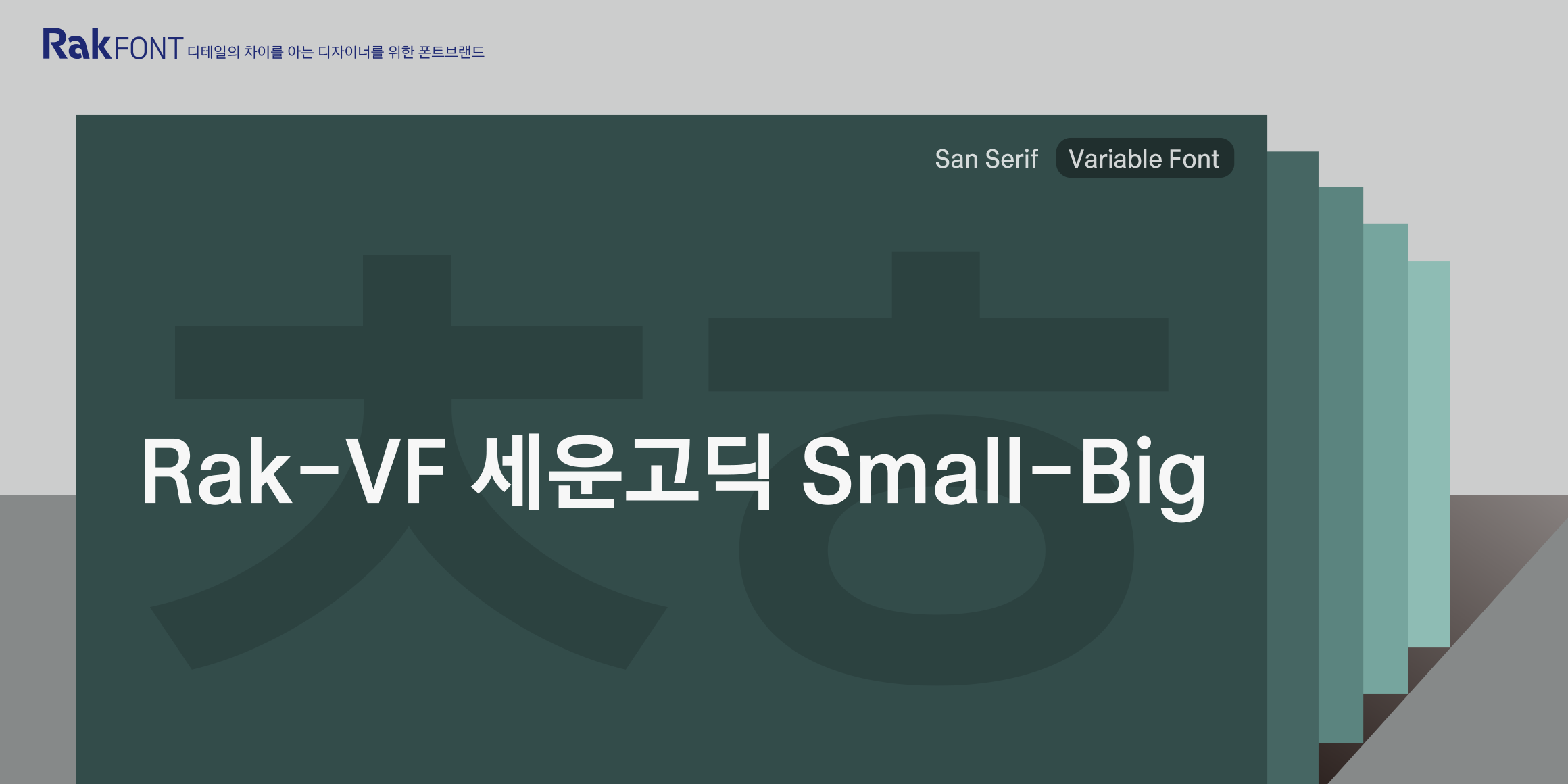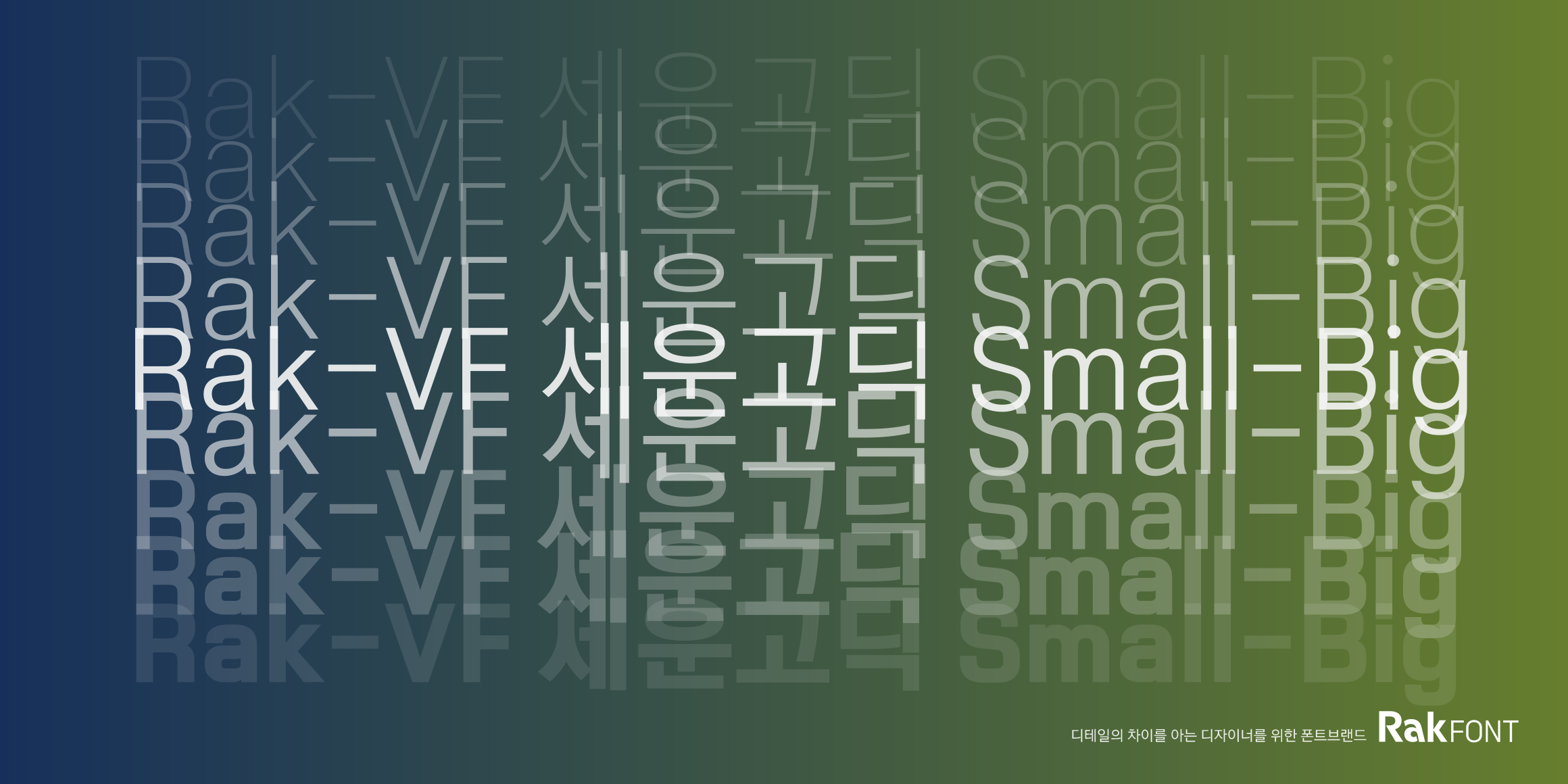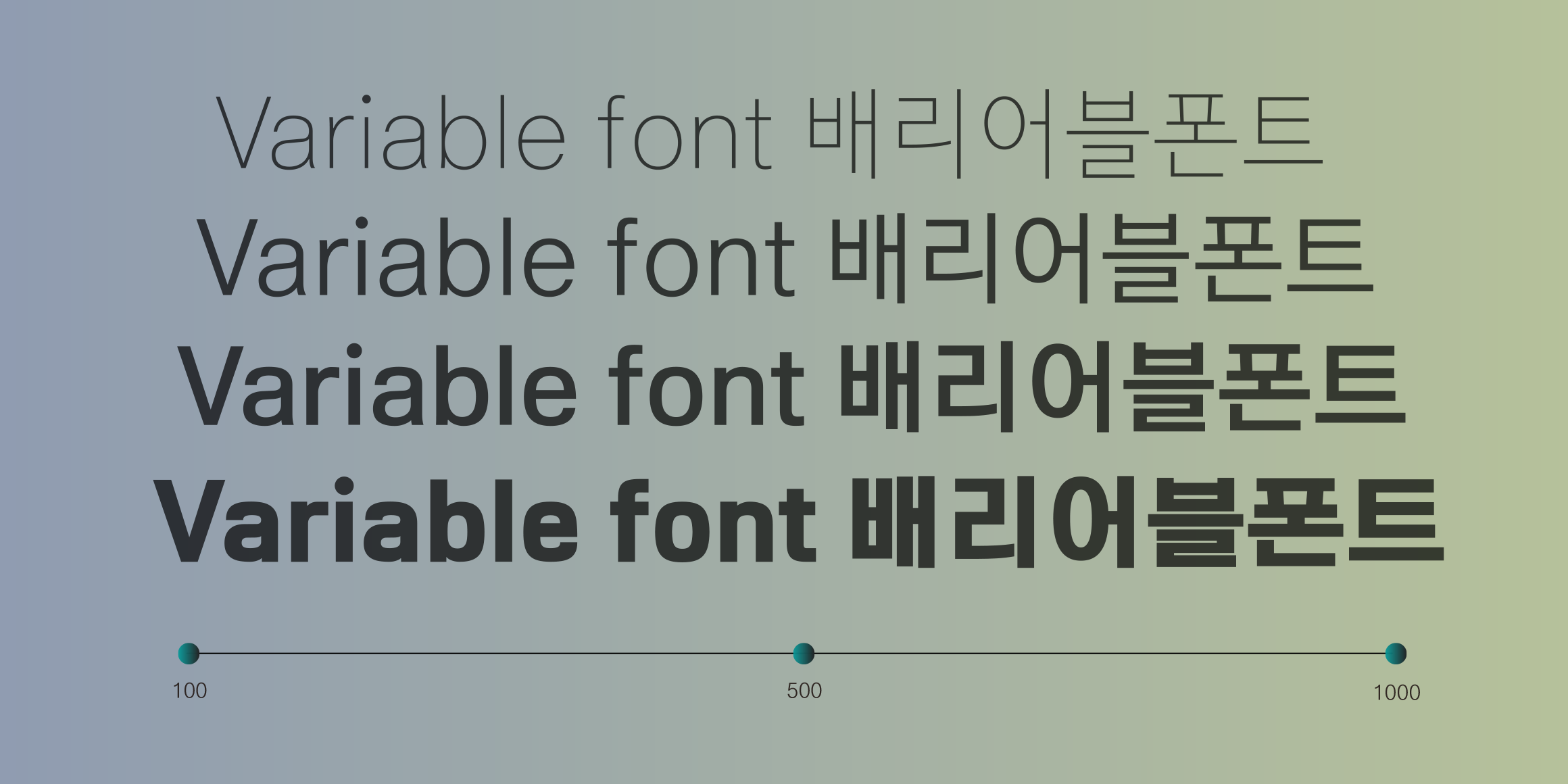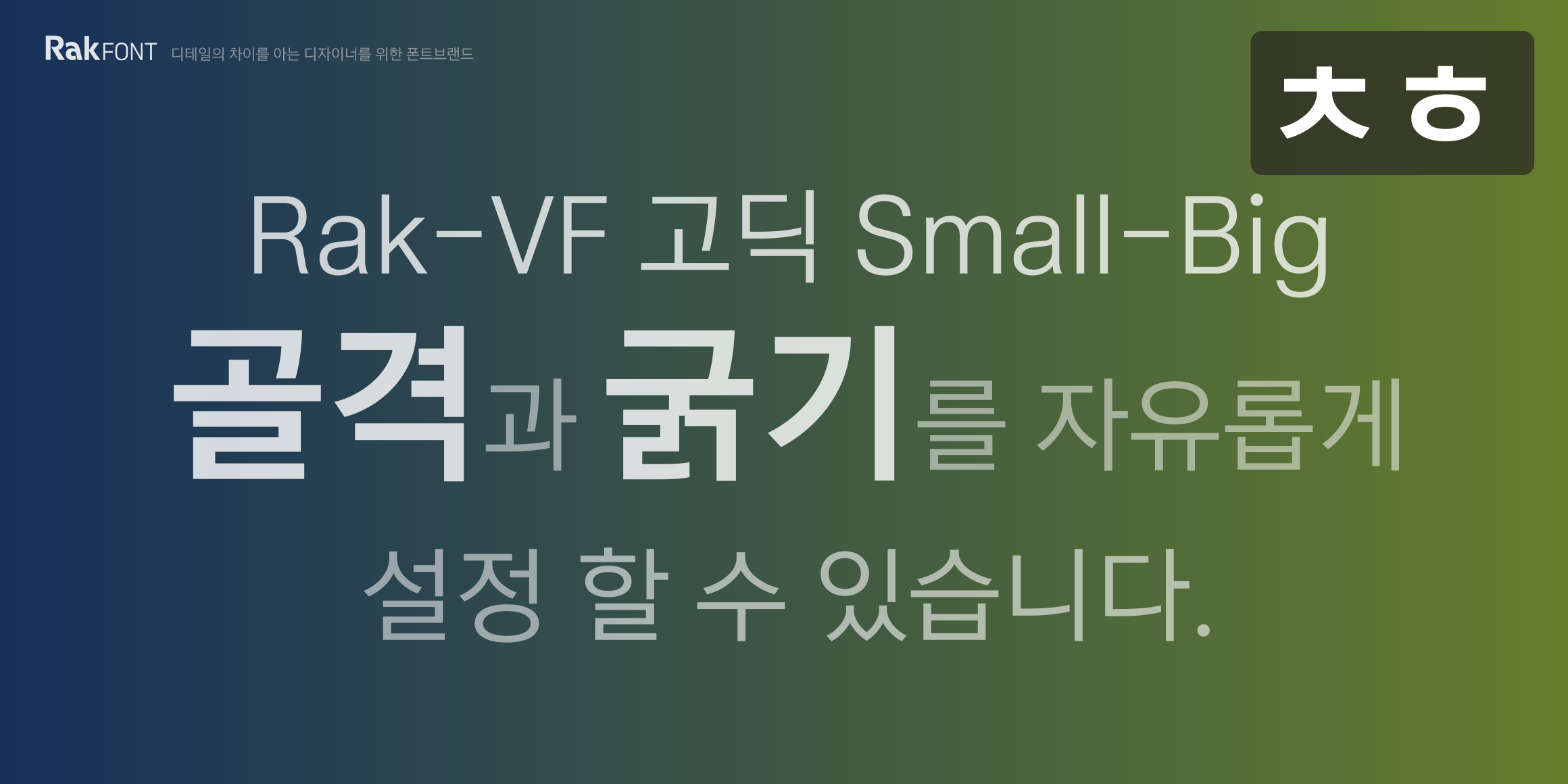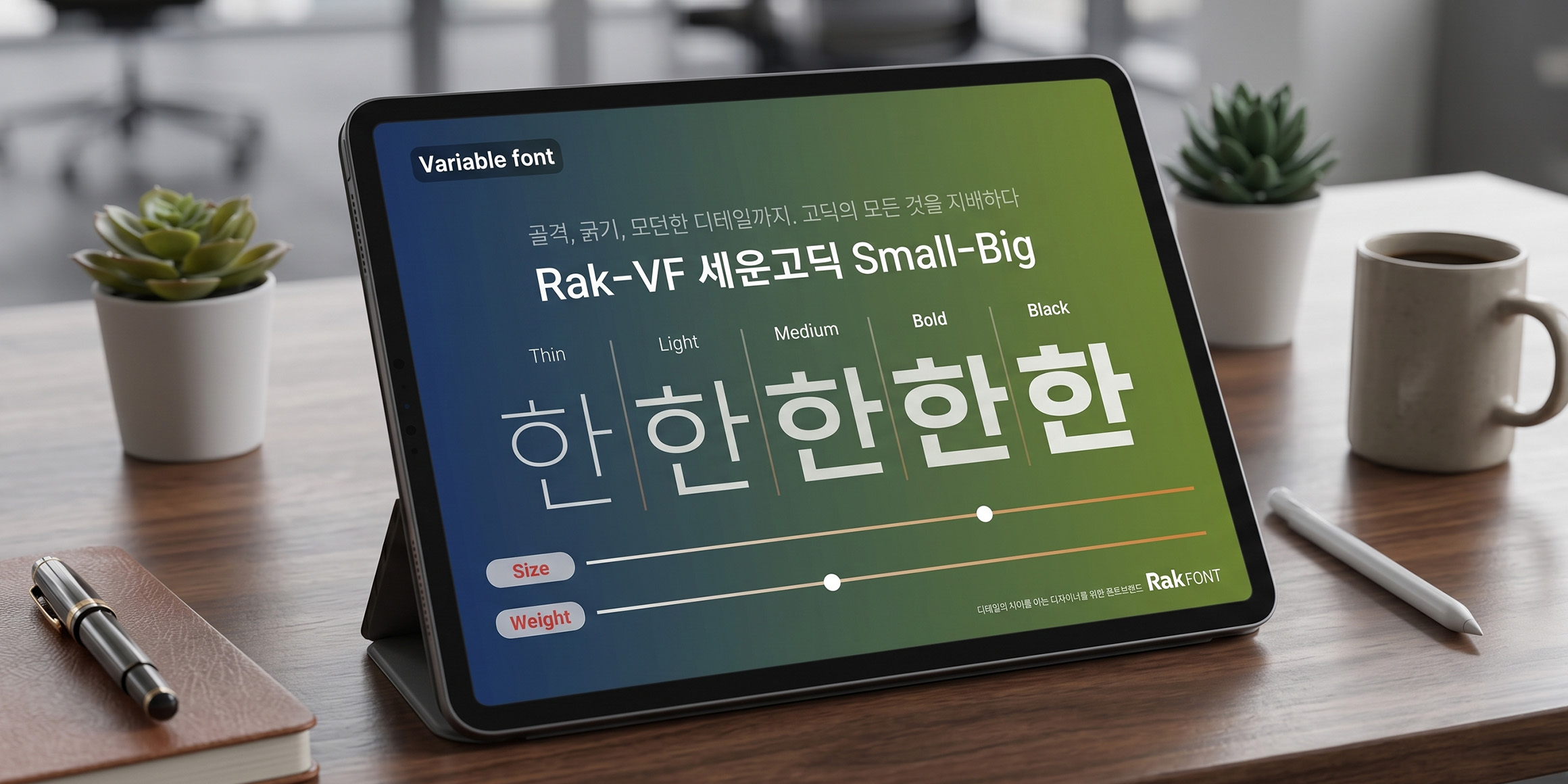
Variable
여유로운 골격부터 꽉 찬 골격까지, 그리고 미세한 굵기 조절까지 단 하나의 배리어블 폰트에 모두 담았습니다. 'ㅊ'과 'ㅎ'의 세로 꼭지로 모던한 디테일까지 놓치지 않은 이 서체는, 디테일의 끝을 추구하는 하이엔드 디자이너를 위한 궁극의 고딕 솔루션입니다.